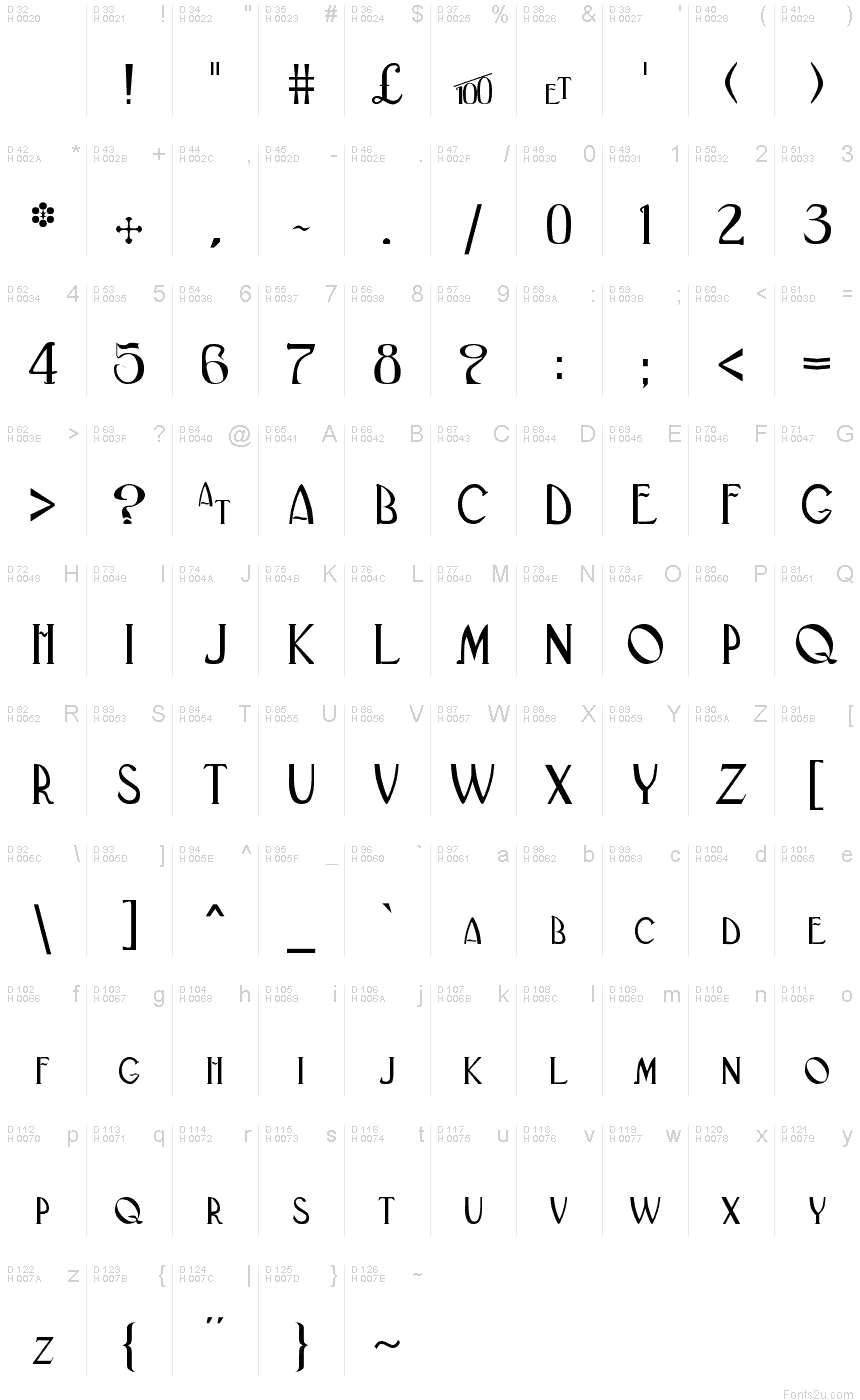
يُعد خط Black Adder II من تصميم Bruce Marx خط عرض مجاني بنمط ريترو يفيض بمشاكسة مسرحية. تبدو حروفه الطويلة والمدببة وكأنها عناوين مكتوبة يدويًا لدراما تاريخية غامضة؛ فهي تتميز بضربات حبرية داكنة، وزوائد حادة تشبه الخناجر، وإيقاع غير منتظم قليلًا يلمح إلى وجود مؤامرة خلف الستار. تمنح نسيج الخط طابعًا دراميًا وكأنه تحت أضواء المسرح، مما يضفي على كل كلمة لمسة من المكر والسخرية.
باستخدام خط Black Adder II، يمكنك تحويل العناوين العادية فورًا إلى عناصر جذب للملصقات الخيالية، ودعوات حفلات الغموض، ولوحات إعلانات المهرجانات التاريخية، وقوائم الطعام ذات الطابع الخاص، وأغلفة الكتب أو أقراص DVD، وحتى العلامات التجارية الساخرة. يتألق هذا الخط المجاني عند استخدامه بأحجام كبيرة، حيث تبرز منحنياته الفريدة وزواياه الحادة. وللحفاظ على سهولة القراءة، يُنصح بدمجه مع خط بلا زوائد (سانس سيريف) محايد ونظيف في النصوص الأساسية، ليتولى Black Adder II خطف الأنظار.
خريطة محارف خط BlackAdderII
Freeware by Bruce Marx, 1991, based loosely on the series.